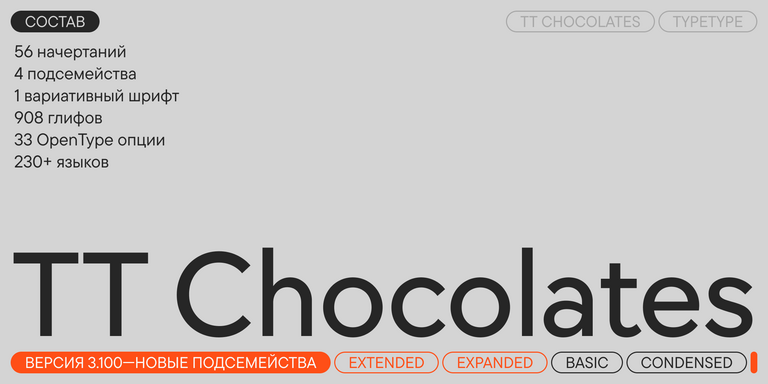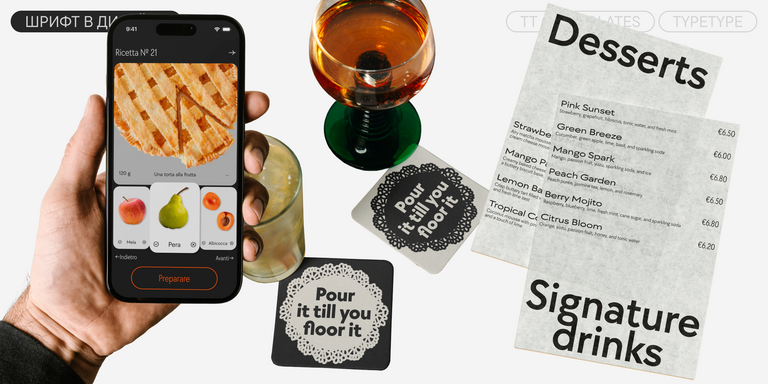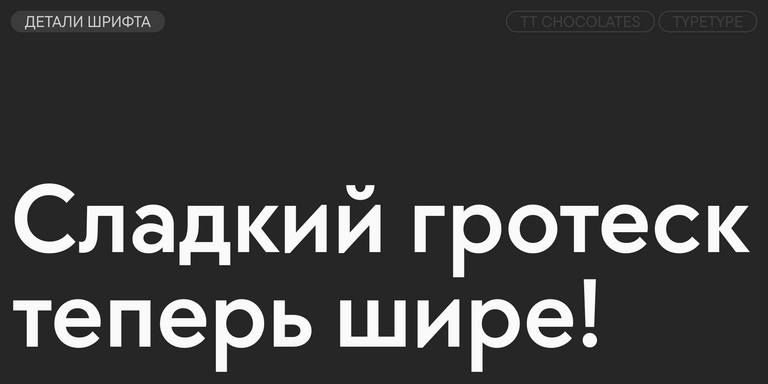
Выберите подходящий шрифт с поддержкой Каталанского языка. Огромная коллекция шрифтовых семейств для любых целей и задач: набор больших текстовых массивов, оформление заголовков для веб-сайтов и печатных изданий, печать на текстиле и других материалах, оформление вывесок и афиш.
Каждый из представленных шрифтов содержит Каталанский алфавит. Широкий выбор символов, знаков валют и пунктуации, шрифтовых начертаний и OpenType фич позволят применять один шрифт для разных проектов. Знаки расширенной латиницы, содержащие диакритические знаки, расширят возможности использования шрифта для разных стран.
Каждый шрифт безупречен с технической точки зрения. Многие шрифты из коллекции содержат вариативное начертание, с помощью которого можно создавать уникальное начертание для проекта.
TT Rationalist — функциональный и оригинальный брусковый шрифт с актуальным рисунком. Он универсален и подходит как для заголовков, так и для массивов текста.
TT Commons™ Classic — универсальный геометрический гротеск для широкого круга задач.
TT Interphases Pro — неогротеск, который создавался специально для работы в интерфейсах. Среди визуальных особенностей TT Interphases Pro — плавные формы скруглений, повторяющиеся во всех элементах: благодаря им большие массивы текста читаются легко и приятно.
TT Octosquares — октагональный гротеск с футуристическим характером. Этот шрифт отличается геометричностью и своеобразной «мозаичностью»: он как бы собран из отдельных фрагментов, что проявляется и в мельчайших деталях.
TT Chocolates — изящный гуманистический гротеск сo сбалансированными пропорциями, близкими к классическим. Шрифт с приятным дружелюбным характером, который интуитивно воспринимается как что-то знакомое.
TT Lakes Neue в версии 2.0 — продолжение геометрического гротеска, вдохновлённого финским функционализмом. Новая версия предоставляет больше возможностей, ведь мы не только увеличили кассовый состав и улучшили шрифт технически, но и доработали его визуальный характер.
TT Rounds Neue — гротеск со скругленными формами. В тонких начертаниях шрифт выглядит довольно минималистично и нейтрально: скругленные окончания штрихов становятся практически незаметными, на первый план выходят плавные линии.
TT Trailers — стильный и выразительный акцидентный гротеск. Его легко узнать по необычной графике: рисунок каждого знака в этом шрифте авторский, формы экспериментальные. Он гармонично смотрится в оформлении афиш и плакатов, идеально подходит для оформления титров. Однако на практике сфера применения этой гарнитуры гораздо шире.
TT Autonomous — современный брутальный технологичный гротеск. Основной визуальной характеристикой гарнитуры является заметная сквадраченность знаков и угловатое внутреннее пространство.
TT Marxiana является проектом по реконструкции набора дореволюционных шрифтов, которые использовались в изготовлении и печати журнала «Нива» 1887 года выпуска, а именно на его антикве и италике, гротеске и эльзевире.